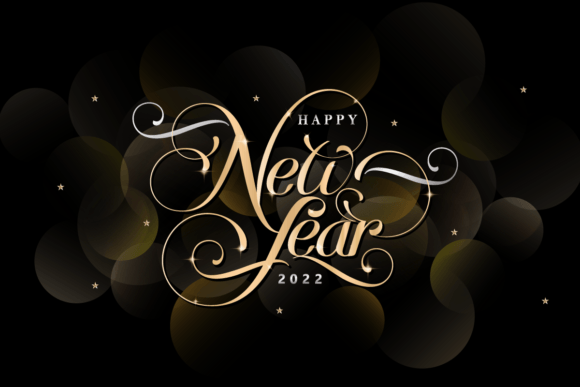
Happy New Year Lettering Fonts
Jika anda sedang mencari aset berkualiti tinggi seperti Happy New Year Lettering Fonts, pakej premium ini merupakan pilihan yang hebat untuk projek kreatif anda.
Dicipta dengan ketepatan, Happy New Year Lettering Fonts menyediakan vektor yang bersih, tipografi yang licin dan lesen komersial untuk ketenangan fikiran.
Sama ada anda mencipta produk POD (Print on Demand), jemputan perkahwinan atau grafik media sosial, Happy New Year Lettering Fonts amat bersesuaian.